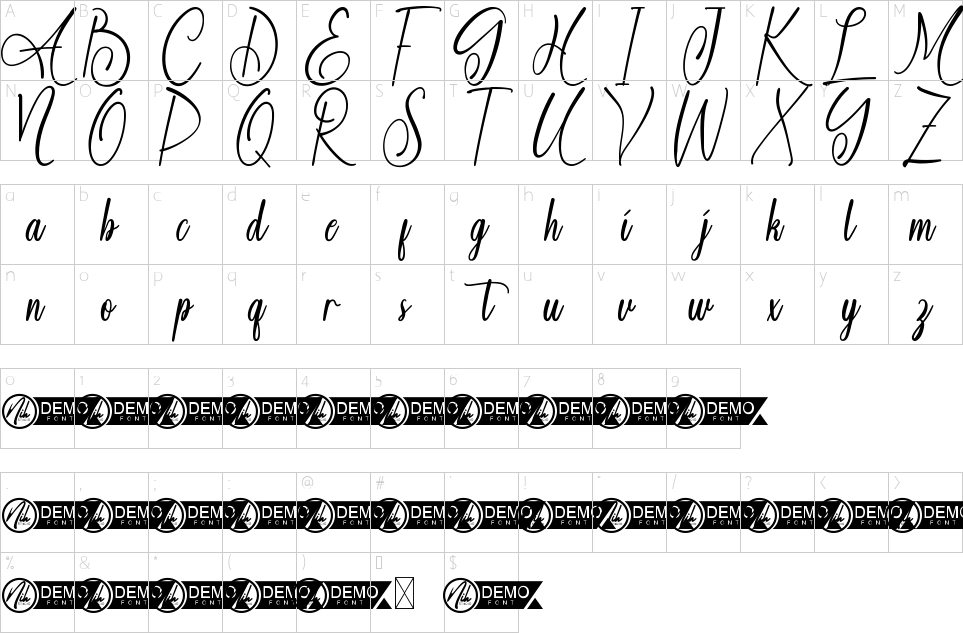
Descubra a beleza única e autêntica da Ariantani Font. Desenvolvida por NihStudio, esta elegante e sofisticada fonte traz consigo uma série de características únicas que certamente enriquecerão qualquer projeto de design. Com uma aparência fluida e arredondada, a Ariantani é perfeita para criar textos atraentes e agradáveis ao olho. Seja para projetos de design gráfico, publicidade ou até mesmo para a criação de artigos de estilo, esta fonte é uma excelente escolha. Com mais de 650 downloads, a Ariantani é uma opção confiável e altamente valorizada no mercado de fontes gratuitas. Adquira-a agora e adicione um toque especial ao seu próximo projeto com esta fonte perfeita.